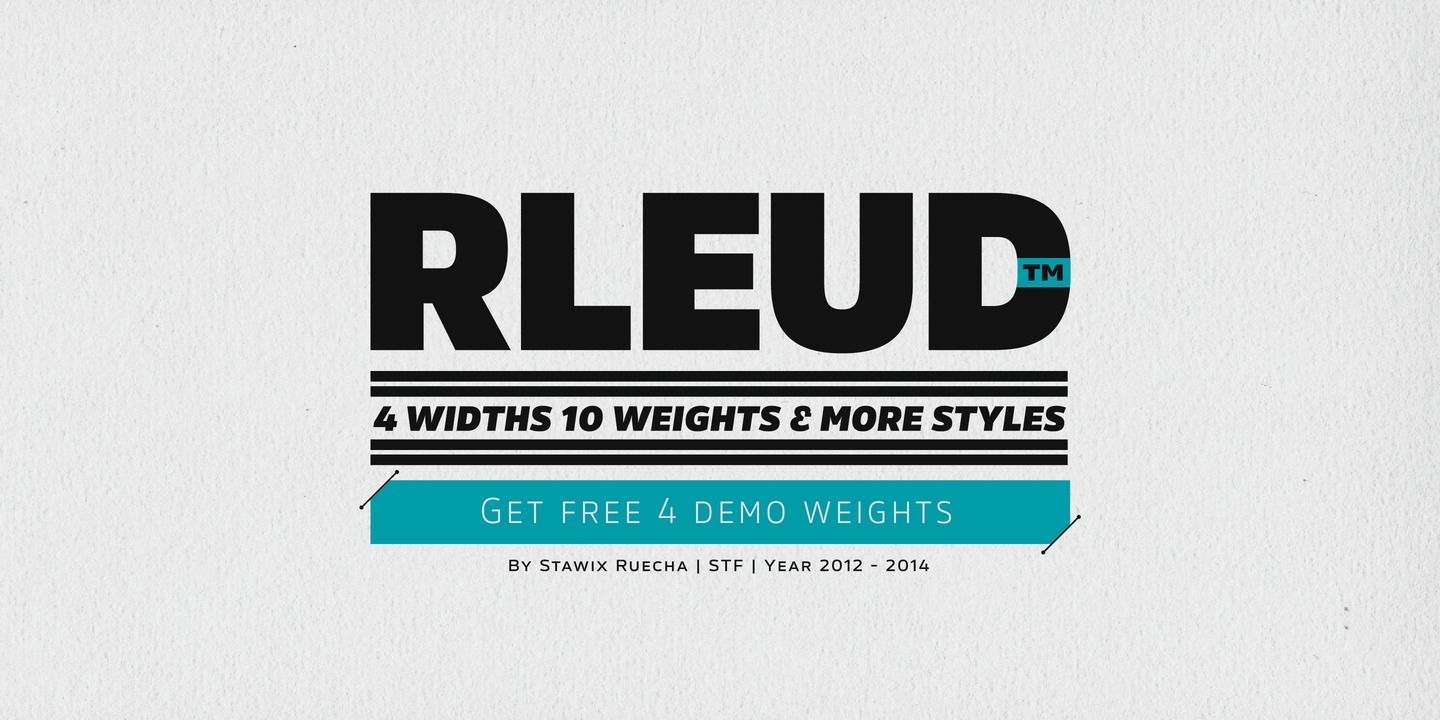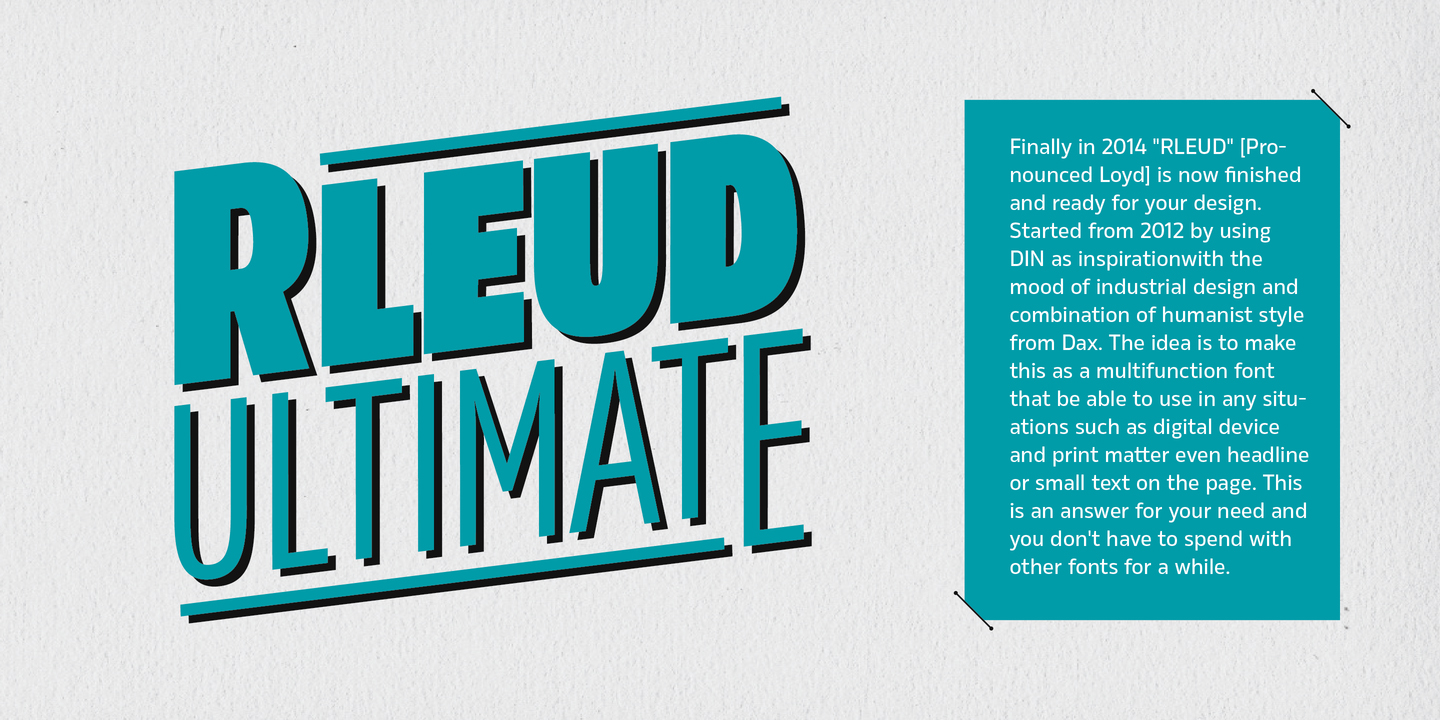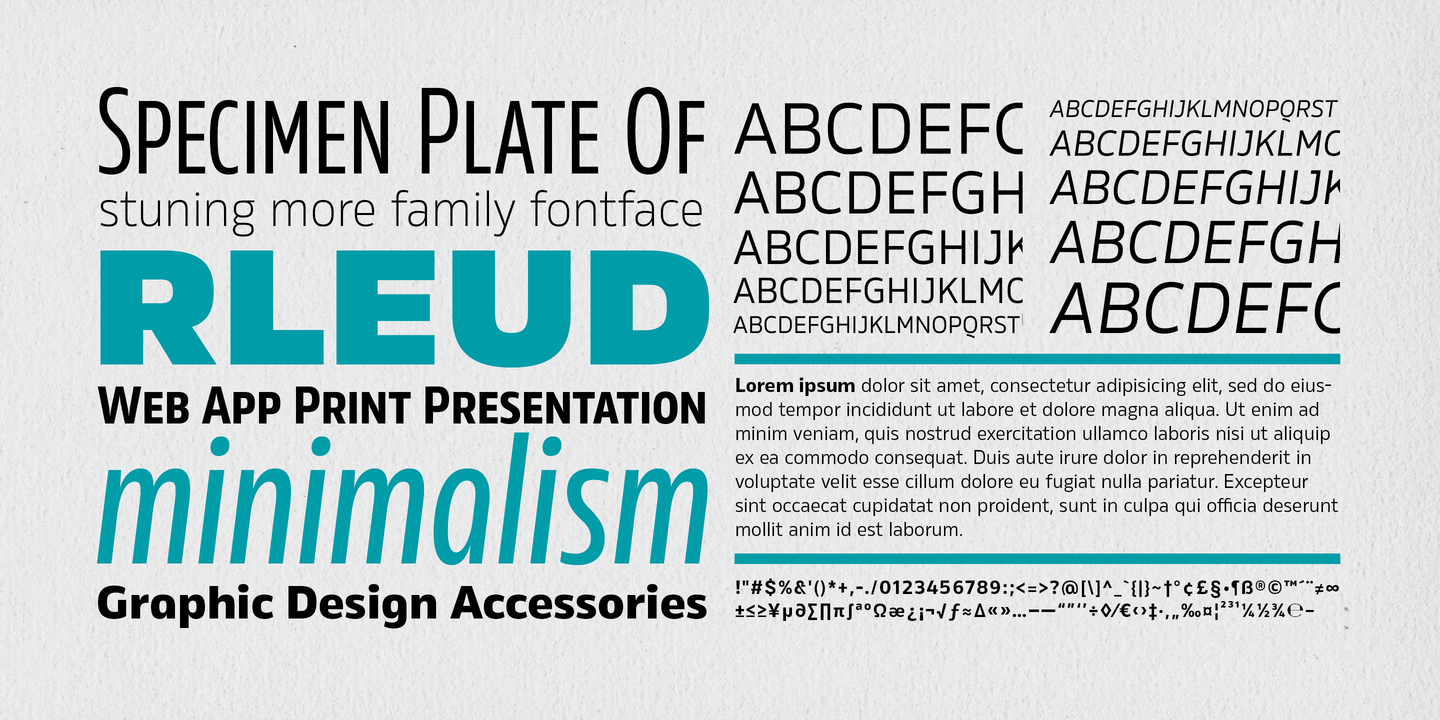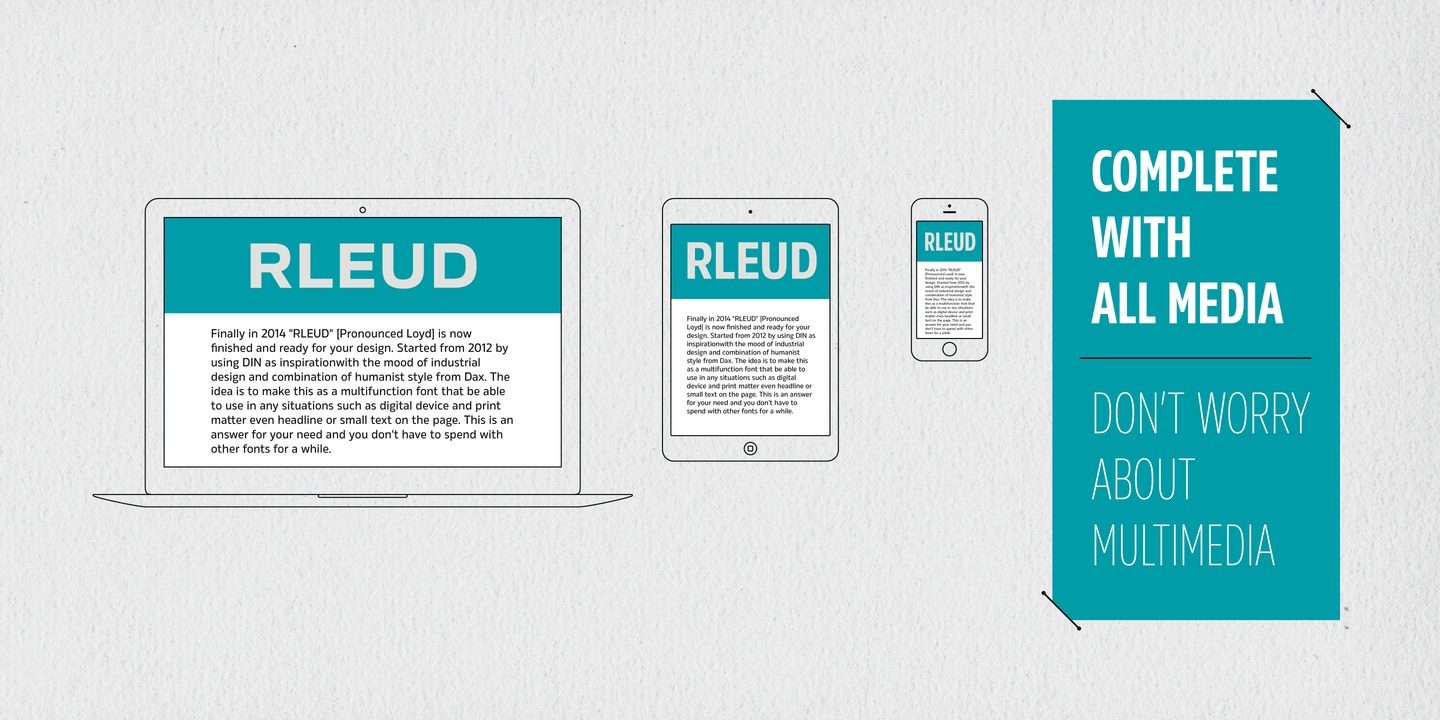
RLEUD là một bộ font chữ rất đẹp ra đời từ năm 2014. Ý tưởng của font chữ làm cho nó trở thành một phông chữ đa chức năng có thể được sử dụng trong mọi tình huống, chẳng hạn như các thiết bị kỹ thuật số hoặc vấn đề in ấn, và thậm chí các tiêu đề hoặc văn bản nhỏ trên một trang.
Phông chữ RLEUD là bao gồm 160 phông chữ: 10 weights với các chữ hoa nhỏ được đặt và chữ nghiêng và 4 kiểu (Normal, Condensed, Narrow và Extended). Các tính năng của Opentype bao gồm các chữ cái thay thế kiểu dáng và chức năng Tabular cho các số, nhiều chữ số hơn và một bản demo với 4 font rất đặc biệt miễn phí.